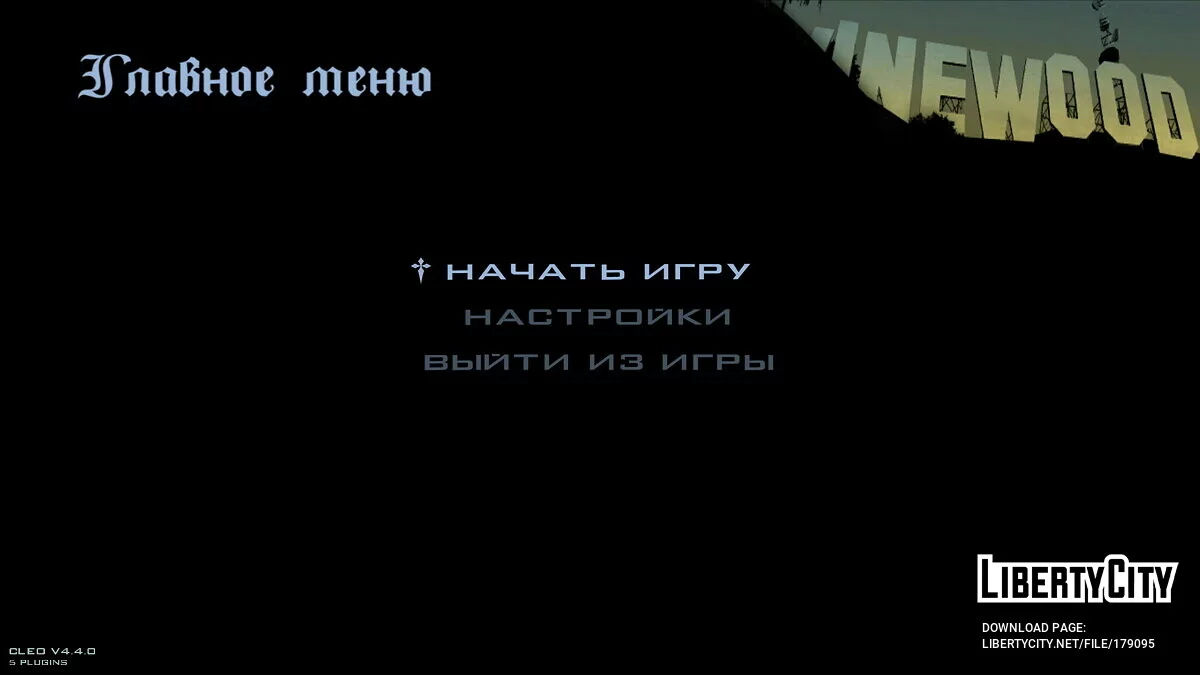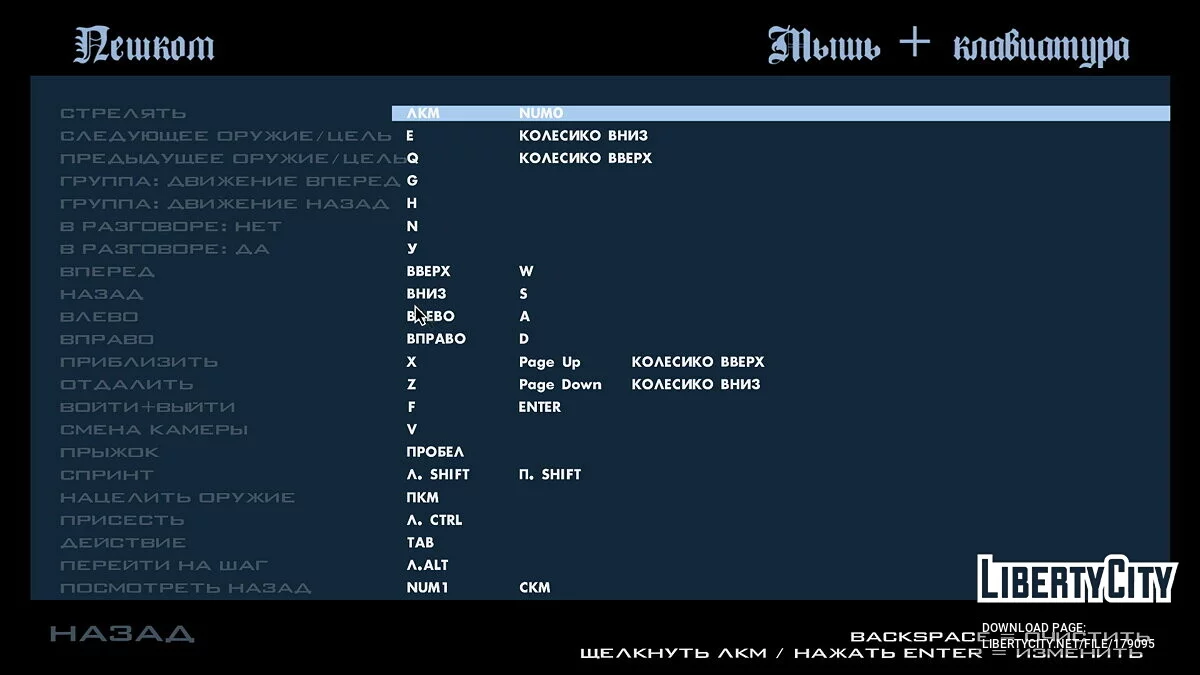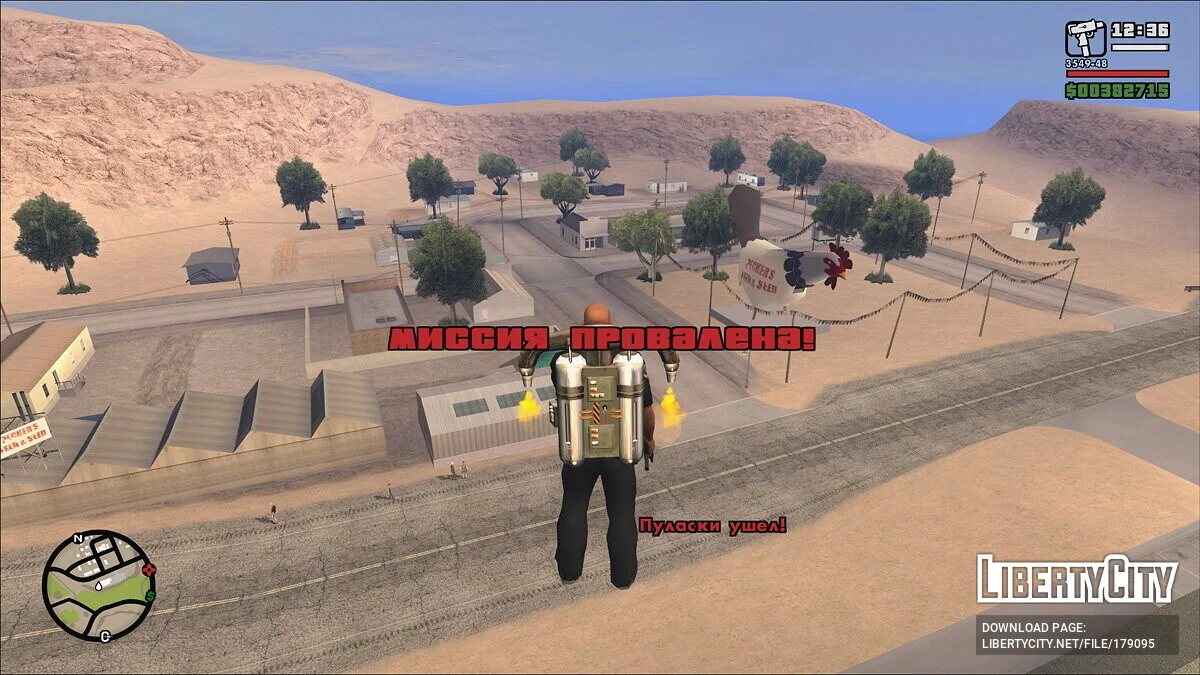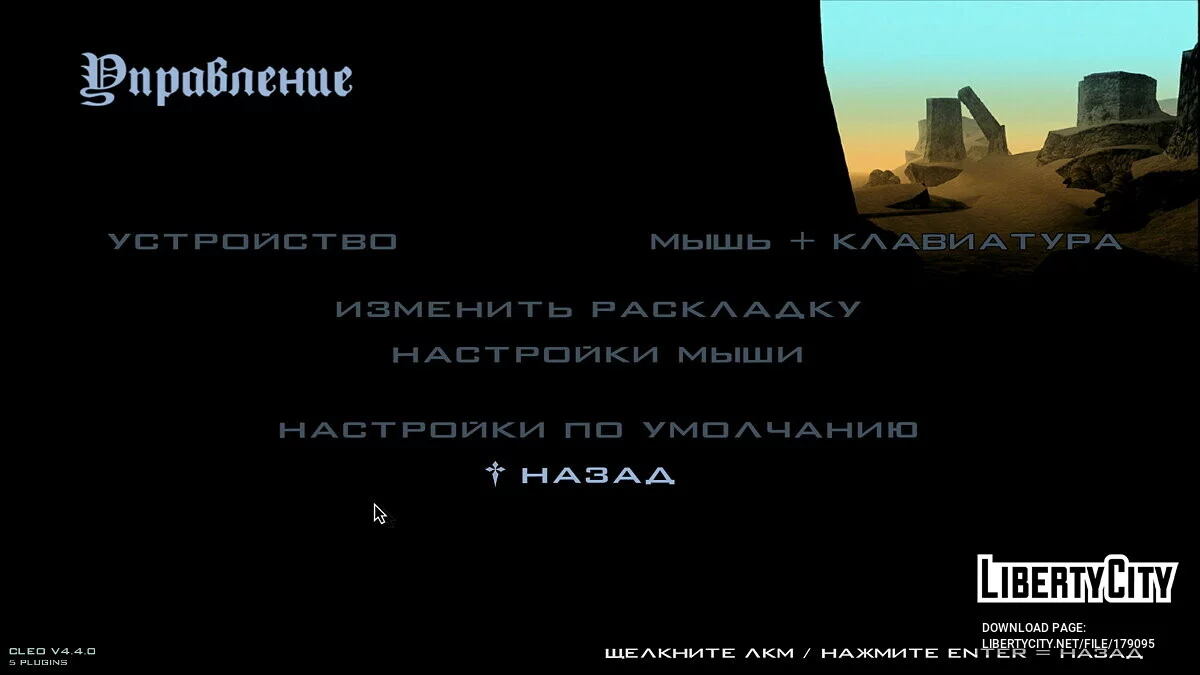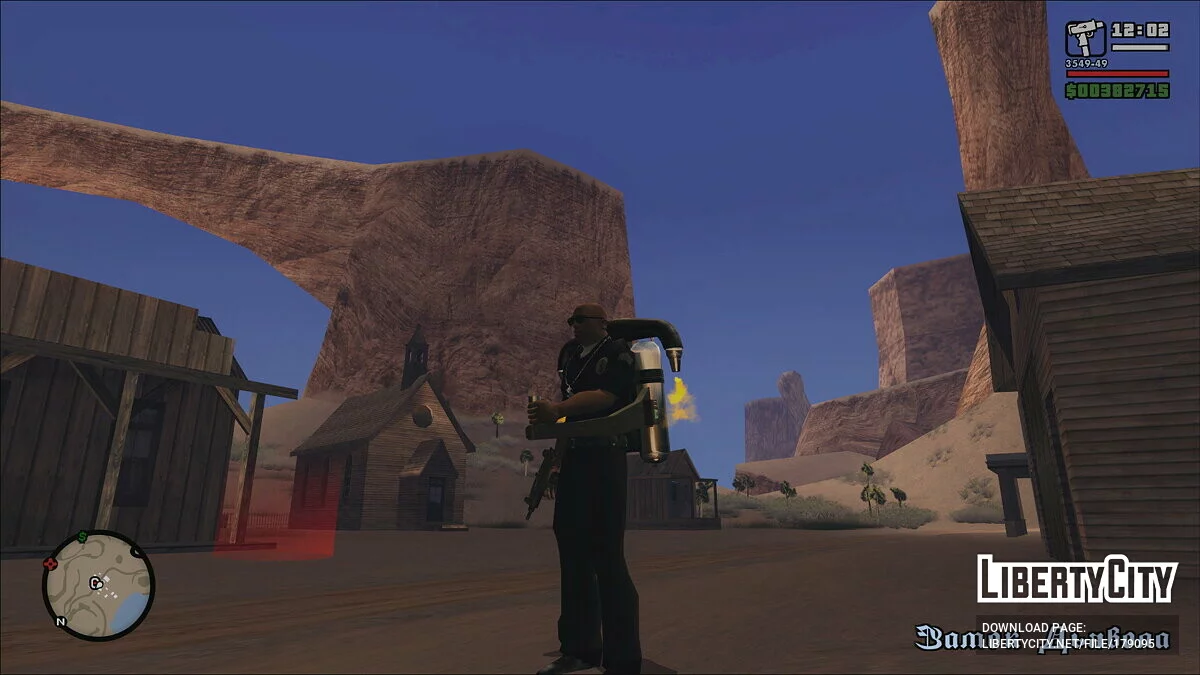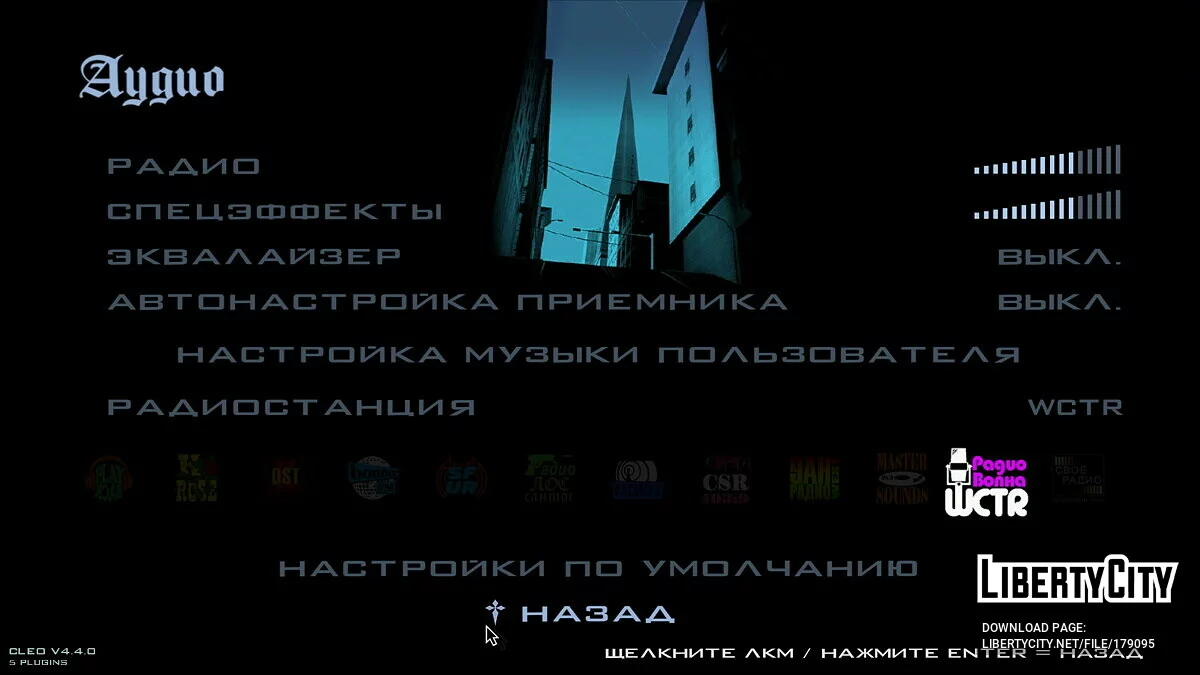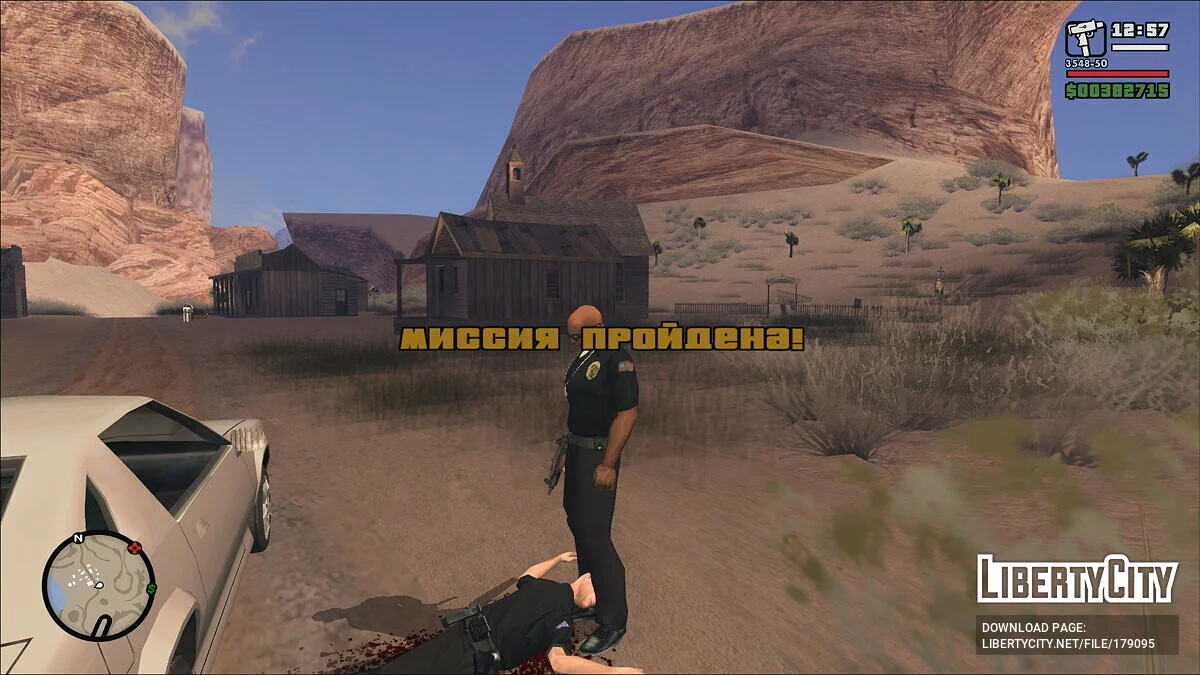
HD-шрифти для русифікатора 1С
Це моя перша спроба щось зробити зі шрифтами (яксь їх покращити).
Формат шрифтових карт 1024х1024рх.
Трохи розставив символи, провів кольорокорекцію, деякі символи постарався зробити, як в оригіналі. Один шрифт перевірив на рівність рядків і рівну висоту символів. Через 2 години мозок луснув. Більше я перевірки поки влаштовувати не буду.
HD-шрифты для русификатора 1С
Это моя первая попытка что-то сделать со шрифтами (как-то их улучшить).
Формат шрифтовых карт 1024х1024рх.
Немного расставил символы, провел цветокоррекцию, некоторые символы постарался сделать, как в оригинале. Один шрифт проверил на ровность строк и равную высоту символов. Через 2 часа мозг лопнул. Больше я проверки пока устраивать не буду.